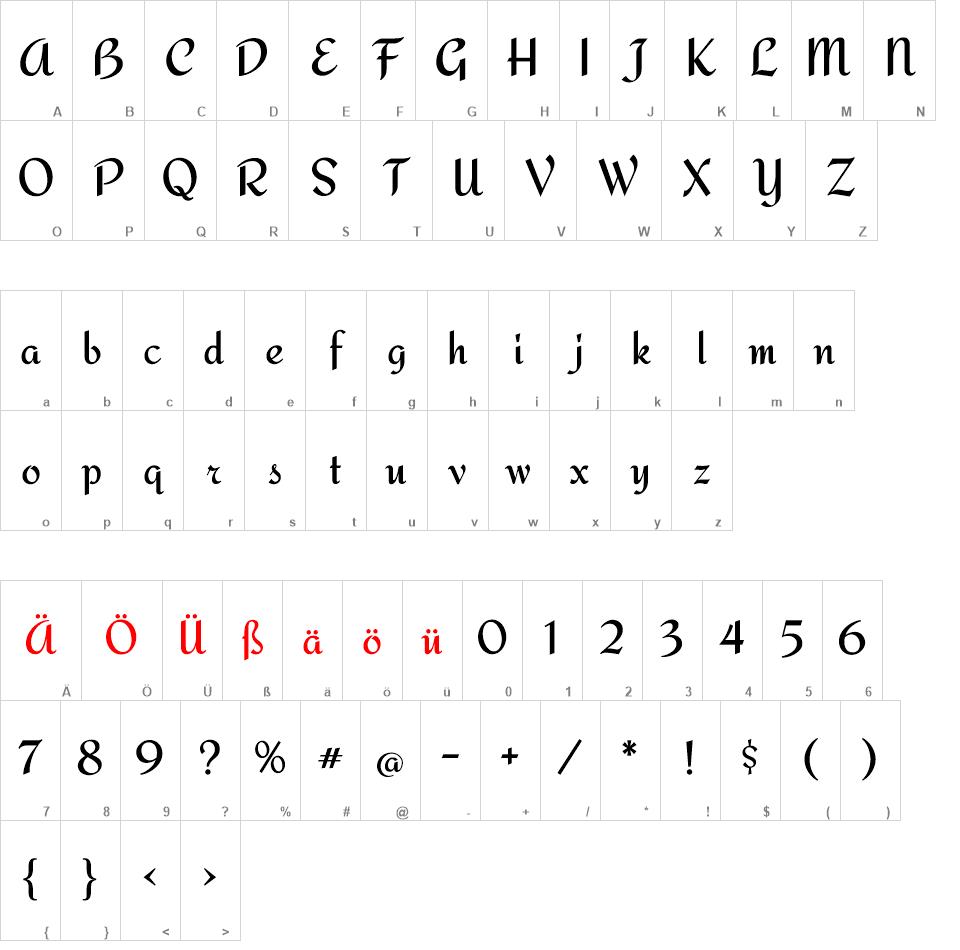
Redressed
Redressed font
Redressed ist eine mittelgewichtige Schrift, die Skript- und Kursivbuchstaben mit einem nicht senkrechten Verknüpfungsstil verbindet. Offene und stilvolle Buchstabenformen ermöglichen es ihnen, sich selbst als Kopfzeilen zu verwenden und gleichzeitig die Lesbarkeit in kleineren Dimensionen als Körperkopien zu verwenden.